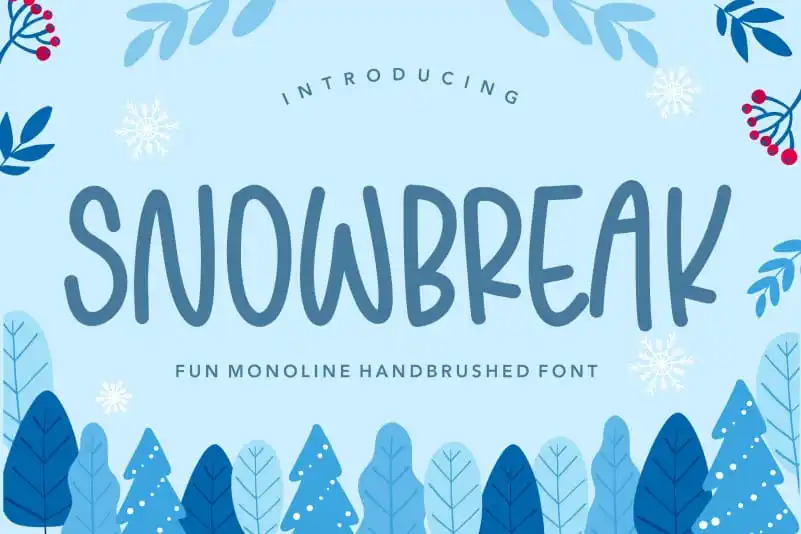
SNOWBREAK Fun Monoline Handbrushed Font – Download Grátis
A Fonte SNOWBREAK Fun Monoline Handbrushed oferece uma experiência única para designers que buscam adicionar um toque moderno ao seu trabalho. Suave e elegante, esta fonte é perfeita para projetos de embalagem de produto, identidade visual, revistas e mídias sociais, além de se adequar perfeitamente para expressar palavras sobre fundo em projetos de casamentos ou qualquer outra ocasião. Com uma aparência delicada que mistura elementos artesanais com linhas clean, ela proporciona um contraste interessante que destaca sua utilização tanto no contexto funcional quanto estético do design gráfico. Este estilo único é perfeito para quem busca criar um ambiente de comunicação visual atraente e inovadora, sem perder o toque humano e personalizado. Completando este leque de possibilidades, SNOWBREAK Fun Monoline Handbrushed é uma escolha inteligente para qualquer designer que deseja trazer brilho à sua criação.